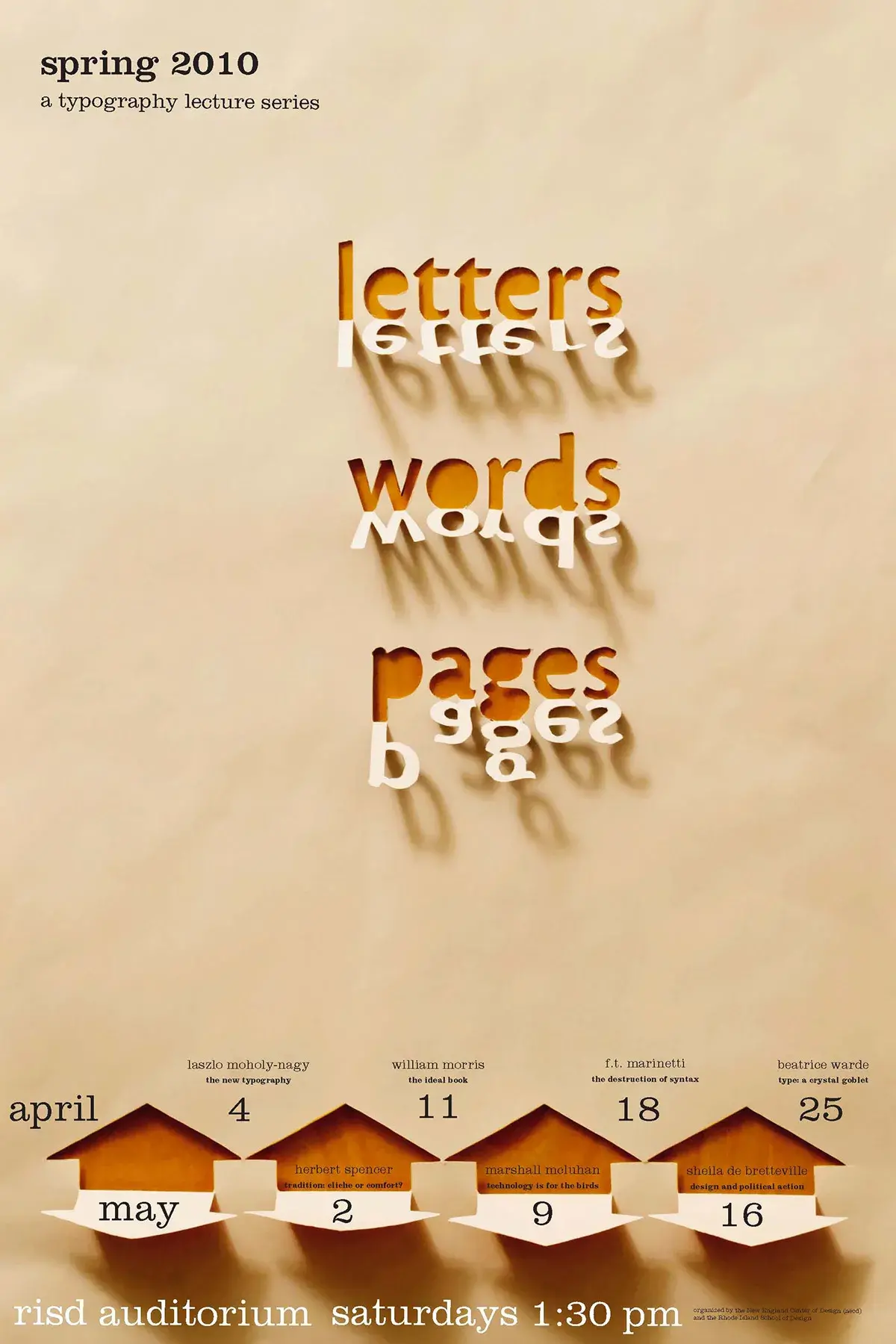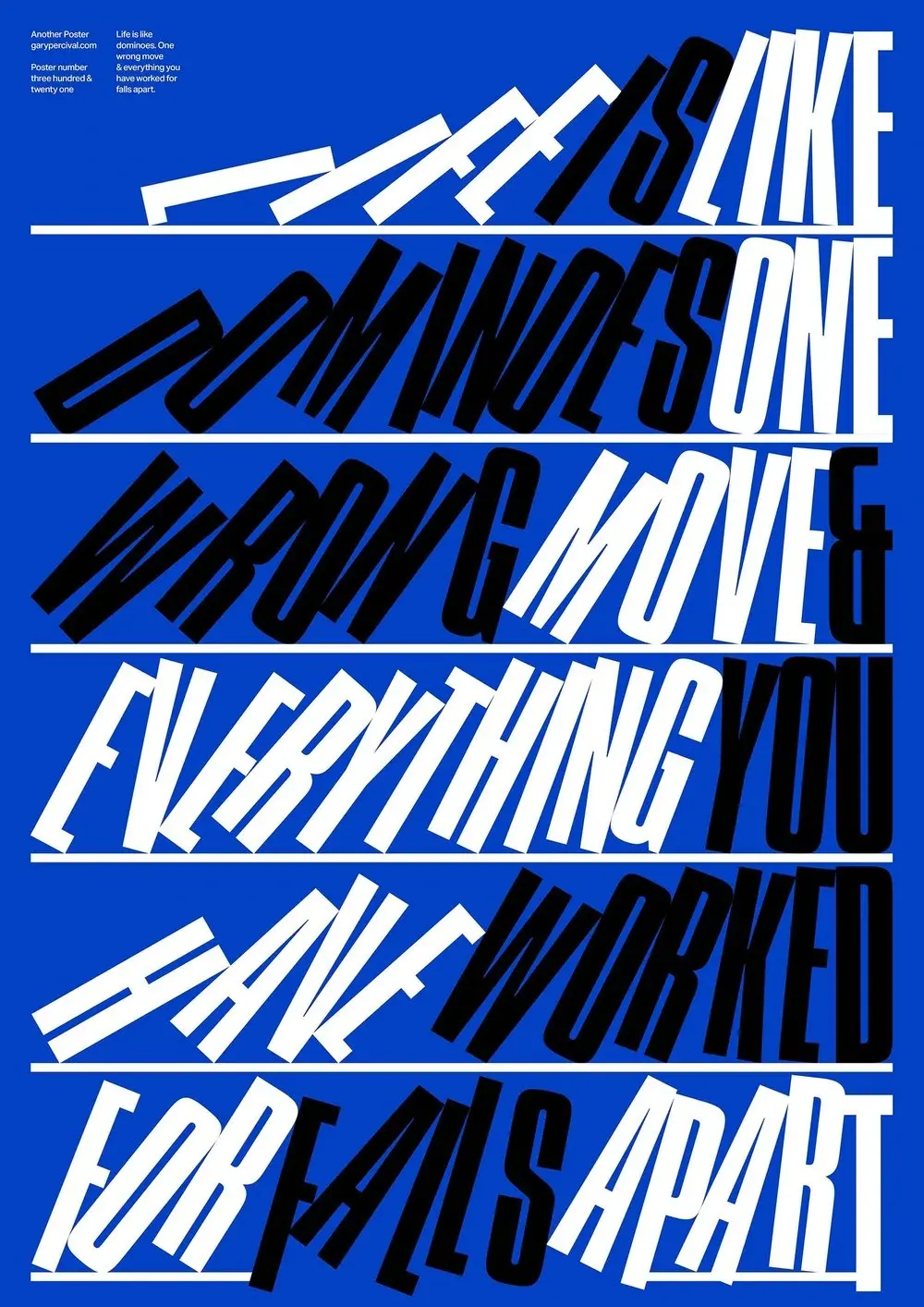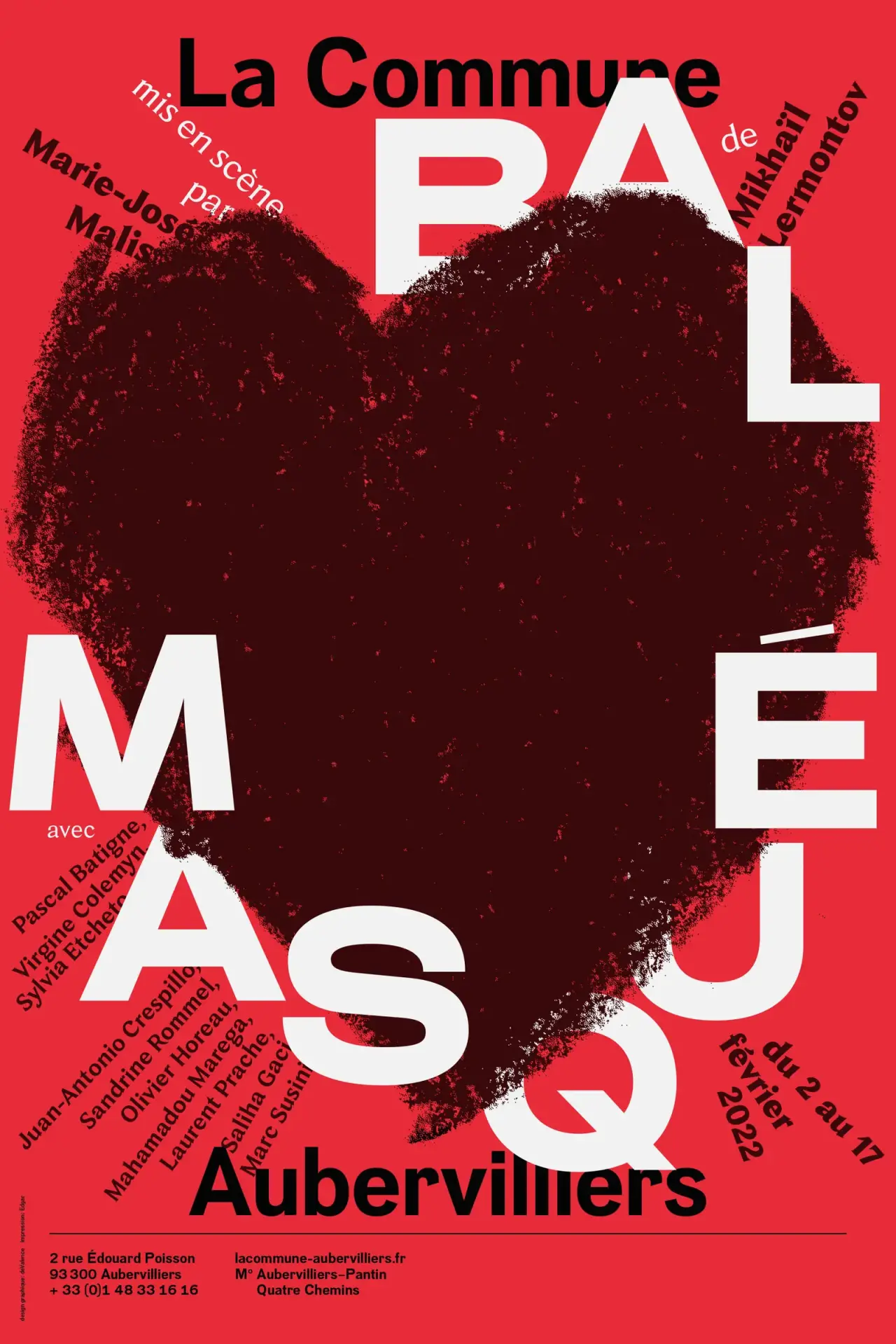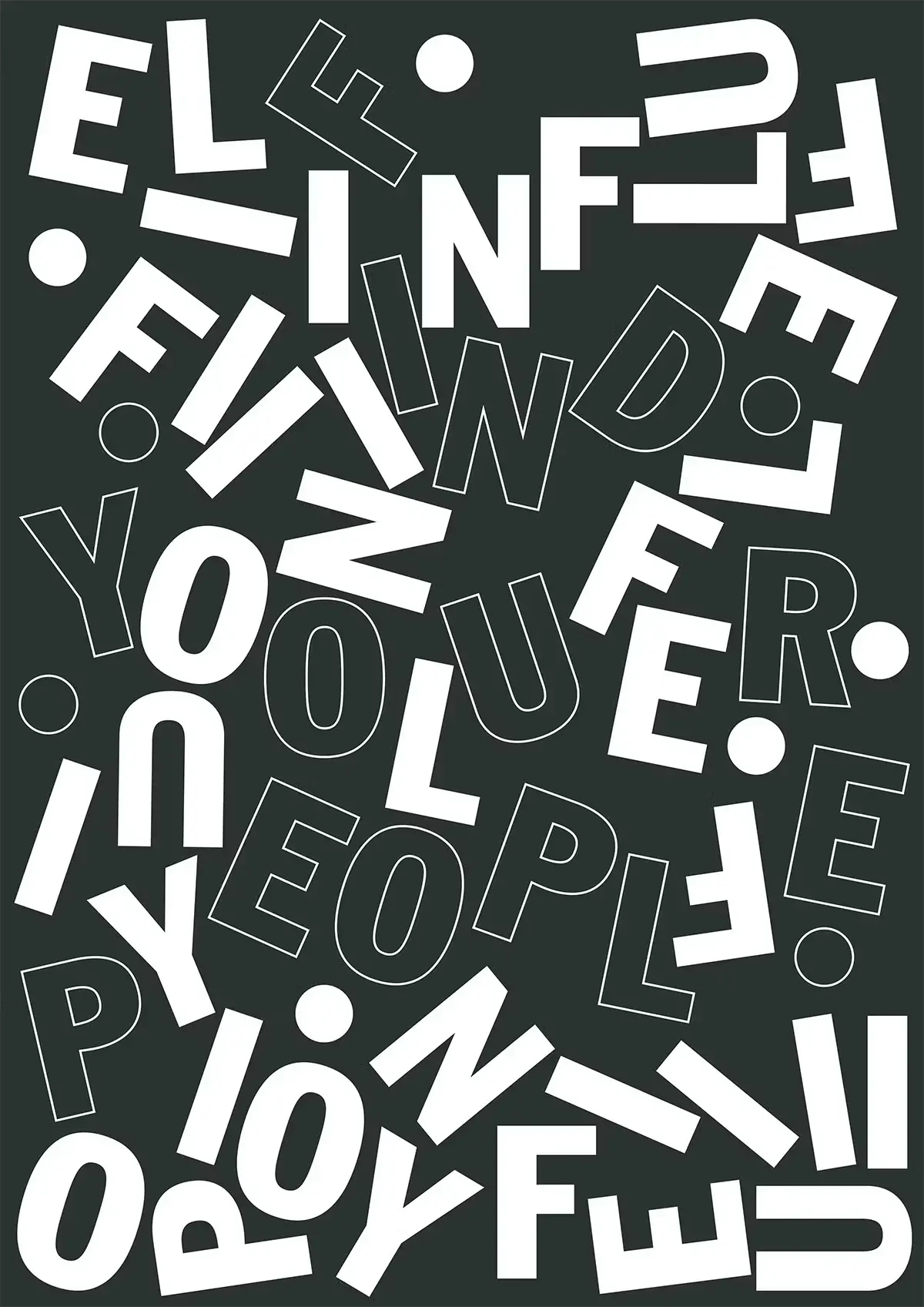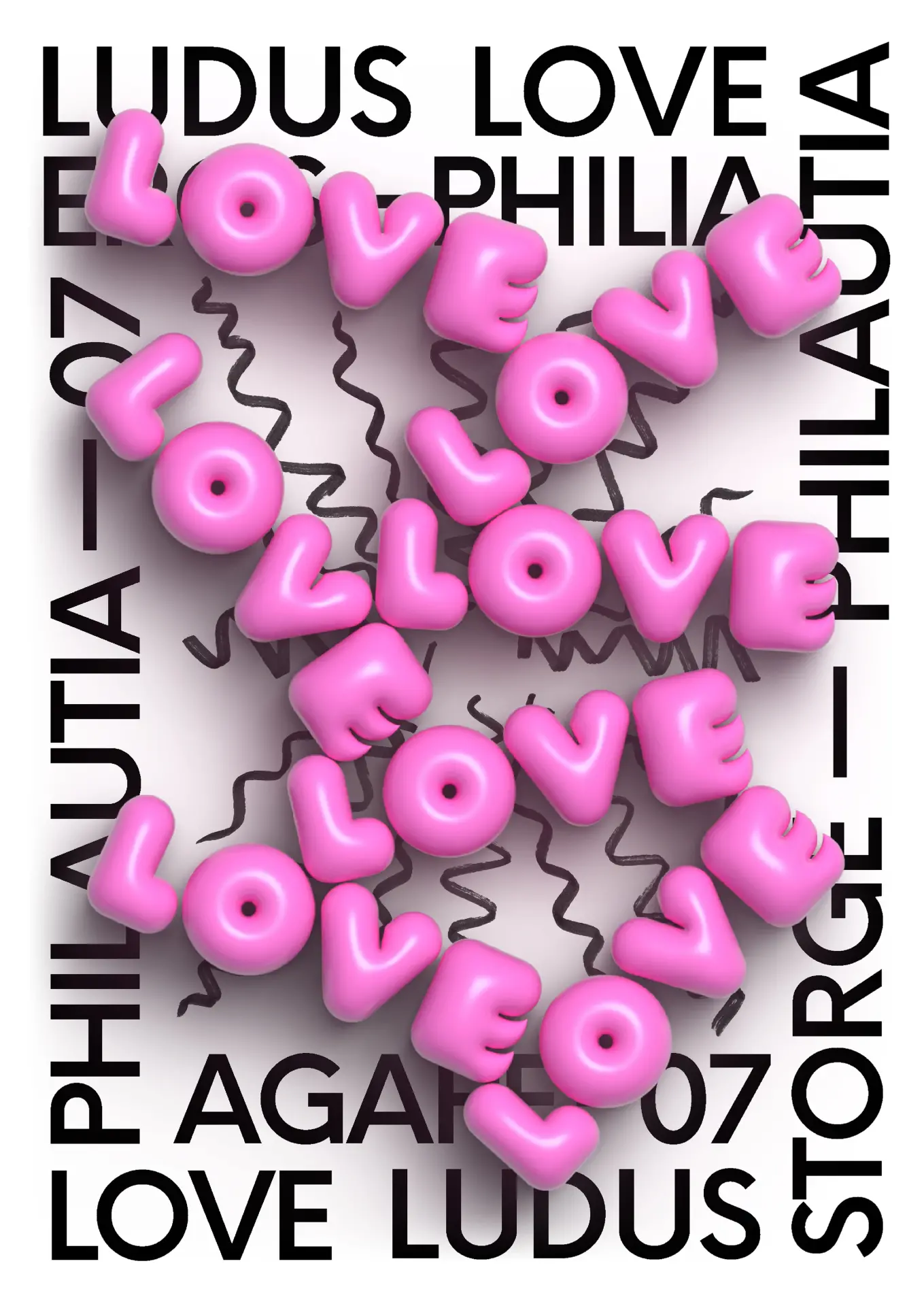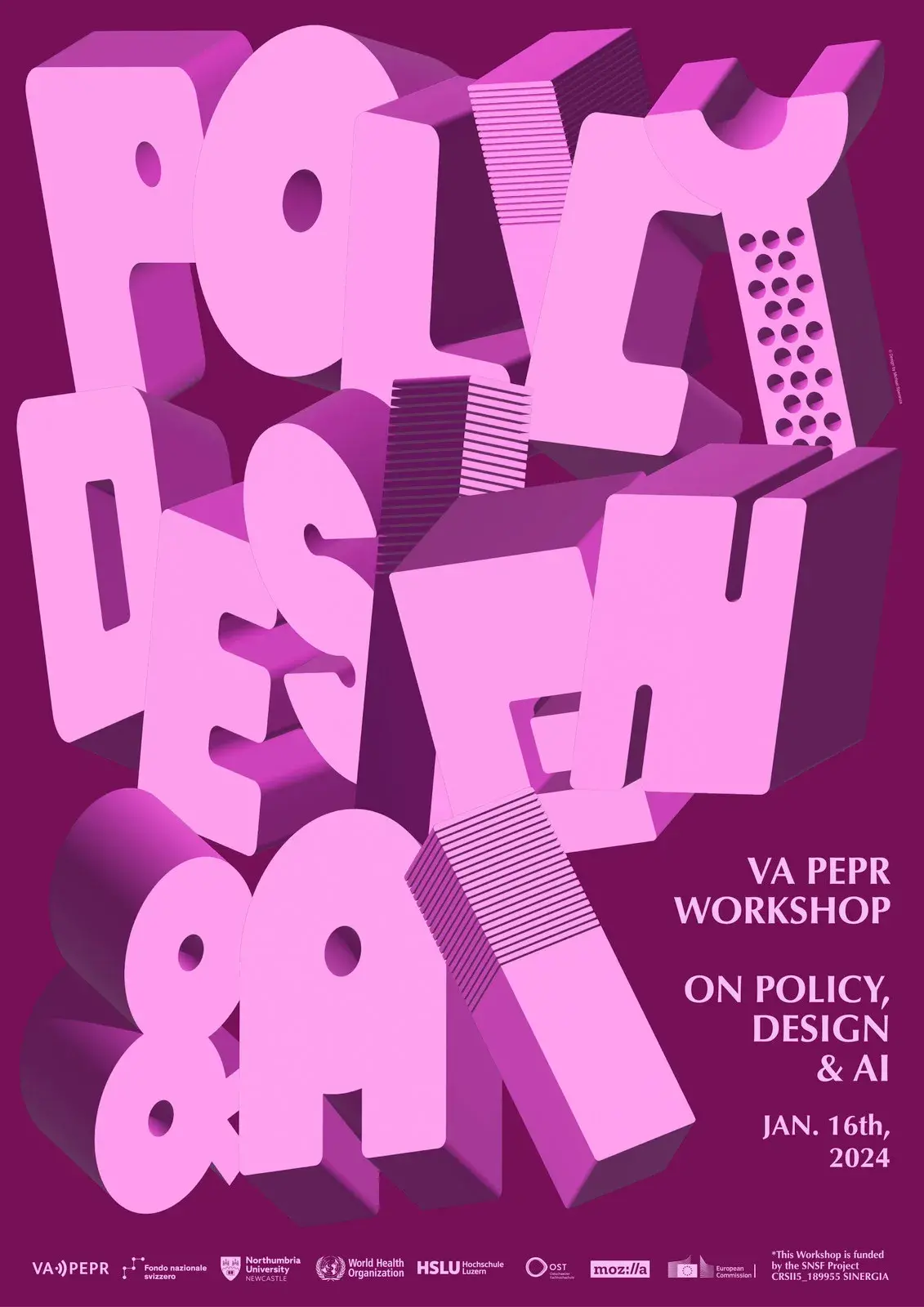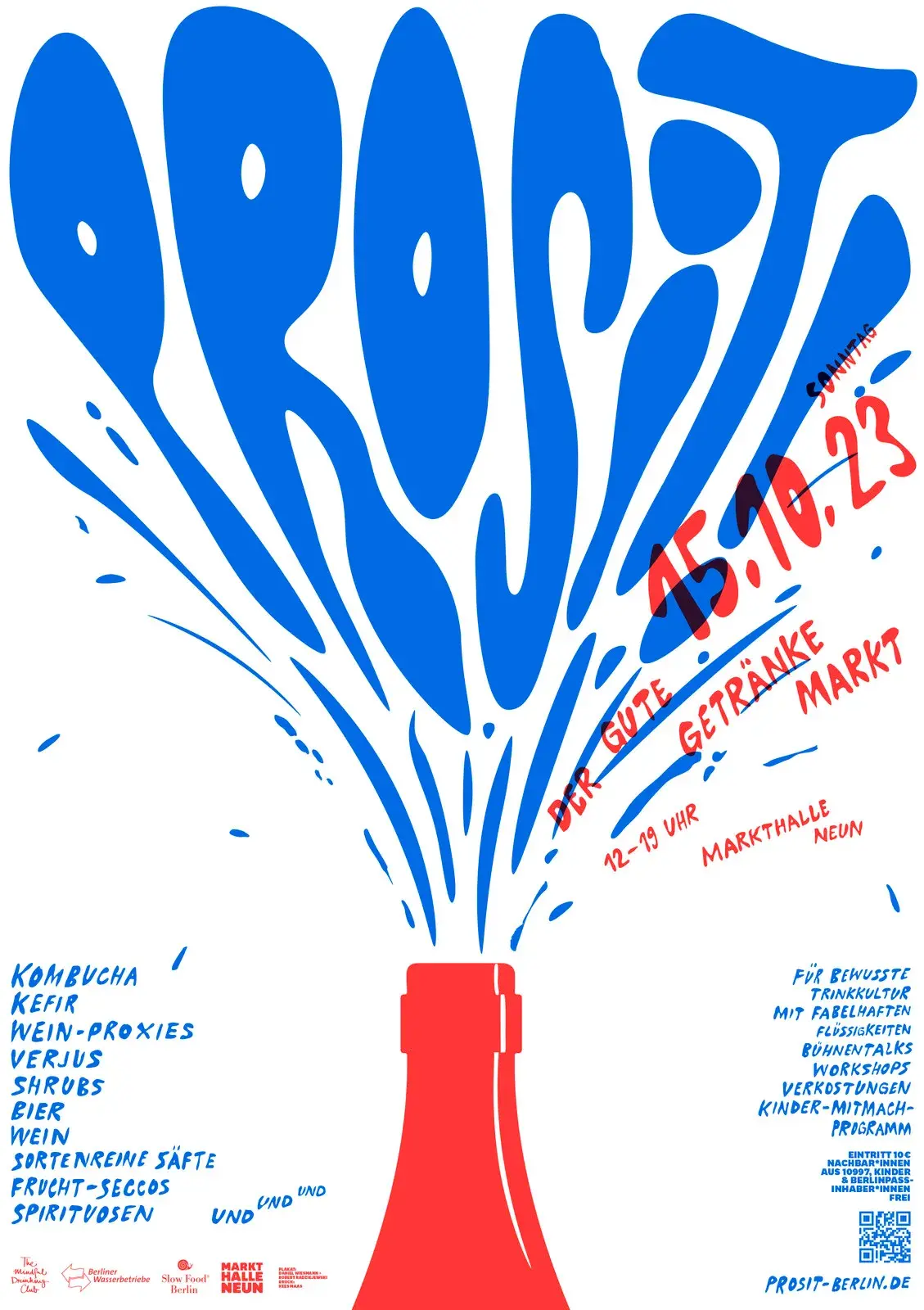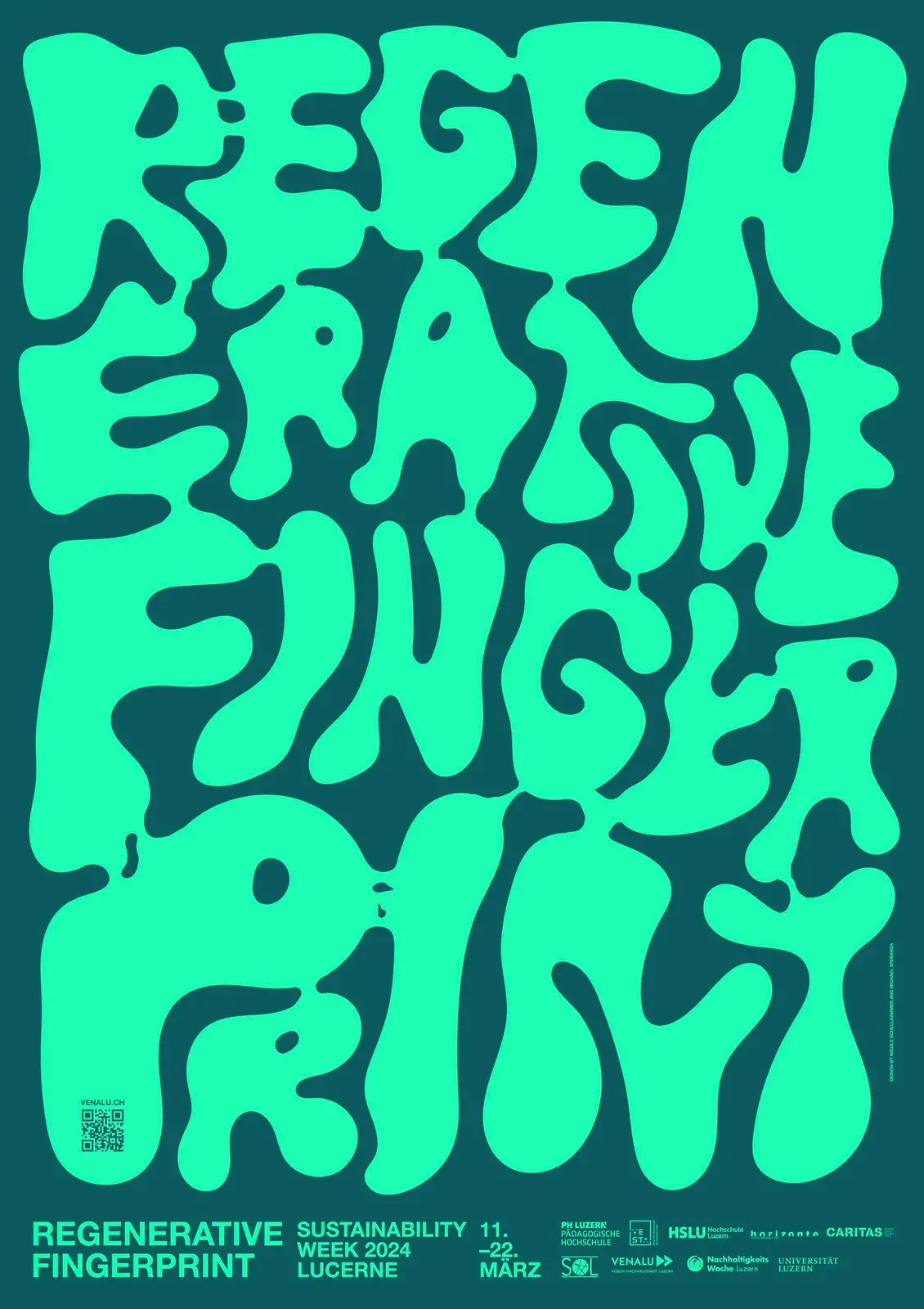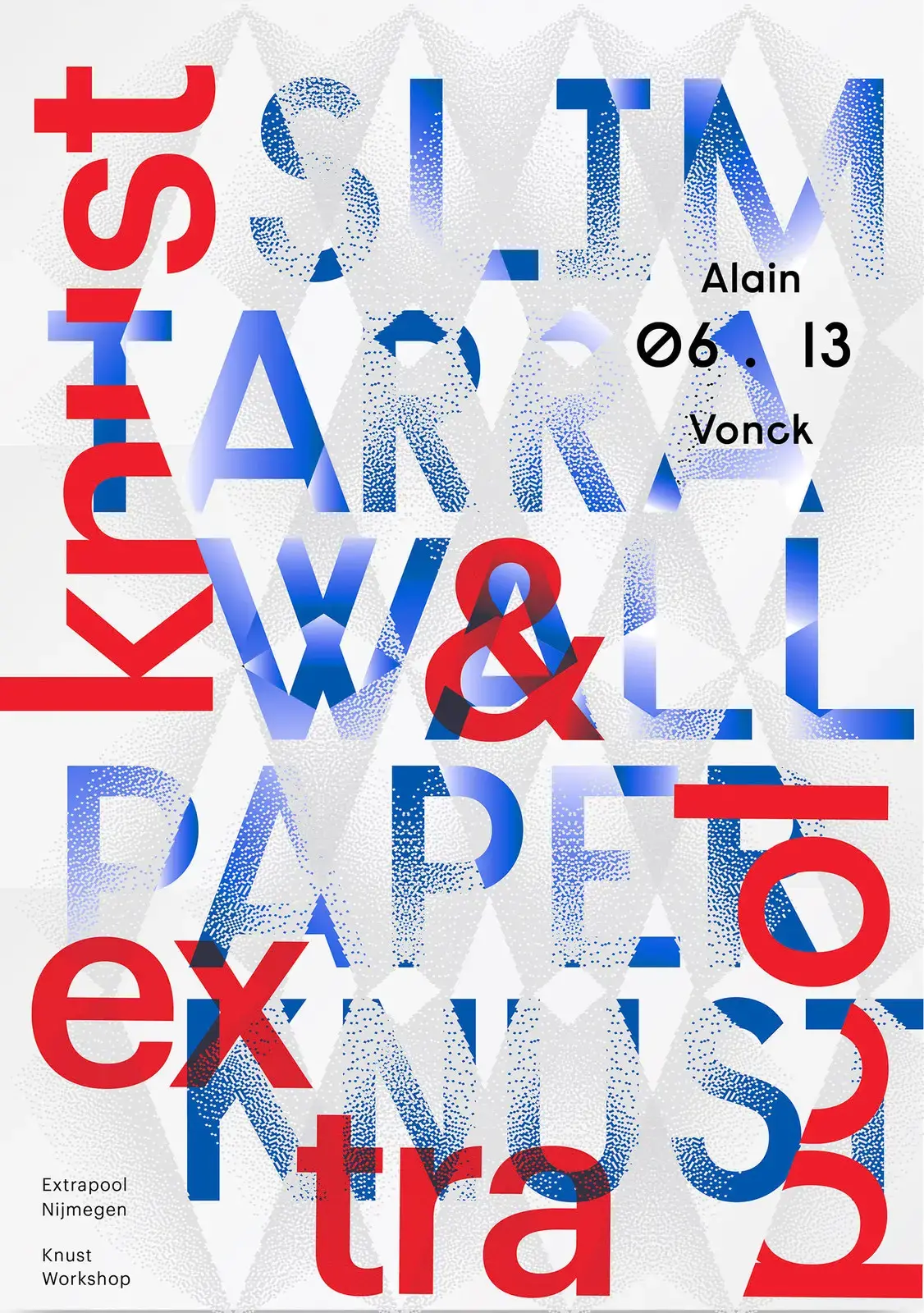
15 affiches typographiques originales à découvrir
Les affiches typographiques ont le pouvoir de transmettre des messages de manière percutante et esthétique. Chaque caractère, chaque espace, chaque couleur est soigneusement pensé pour créer une composition visuelle qui captive l'œil et émeut l'esprit.
Que ce soit à travers une typographie moderne et audacieuse, des nuances subtiles et élégantes, ou une mise en page originale et ingénieuse, chacune de ces 15 affiches possède sa propre personnalité et son propre message à communiquer.
Nous espérons que ces exemples vous apporteront une bonne dose d'inspiration pour la journée et vous aideront à trouver des idées pour vos futurs projets créatifs !
Amnesty International - DDB Paris
Pas trop saignant - Pierre Jeanneau
Regenative Fingerprint - Michael Speranza
The New Art School Rules! - Vicky Carr
Proposal - Stahl R
Policy Design & AI - Michael Speranza
Prosit! - Daniel Wiesmann & Robert Radziejewski
Black Rain - Harry Richards
Love - deValence
FEOS Type Poster - Bogdan Roșu
Love - Nick Barclay
Life Is Like Dominoes - Gary Percival
Irradi 13 Slimtarra 1 - Irradié
Posters Vol II - Xtian Miller
Le livre de la jungle - Mora Prince
On peut tromper mille fois une personne par Le Cartel Français